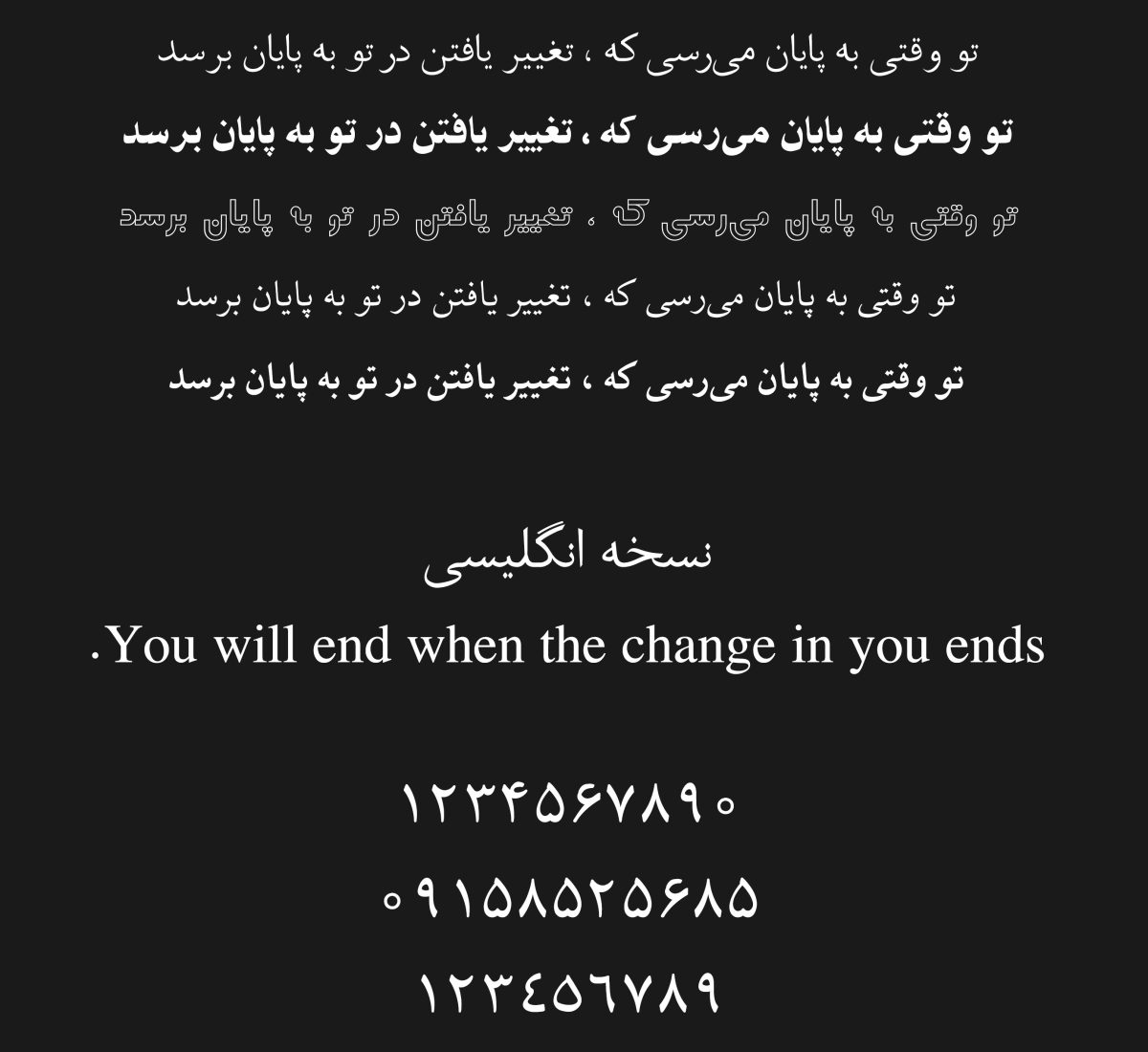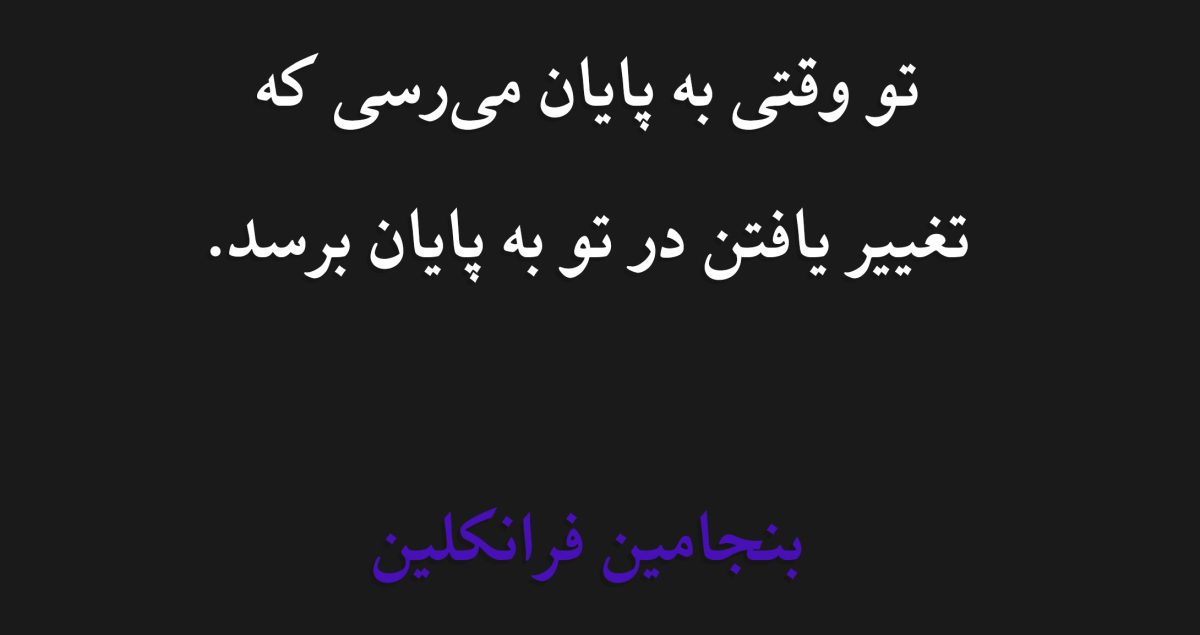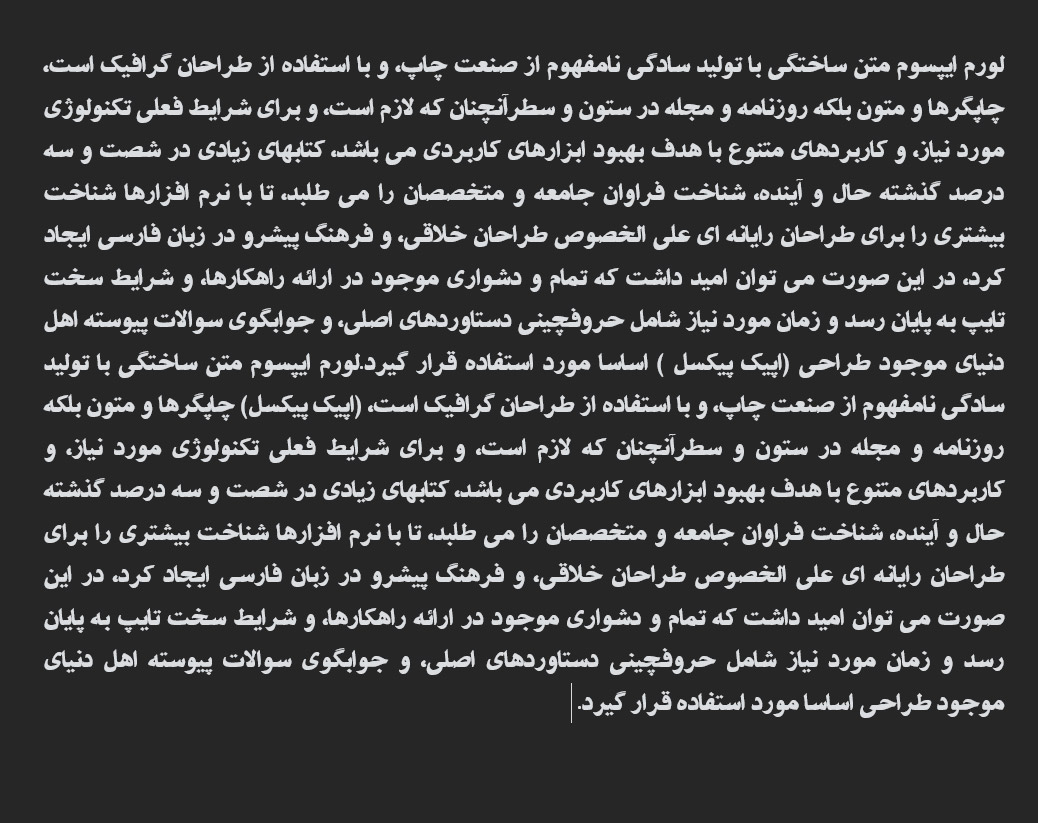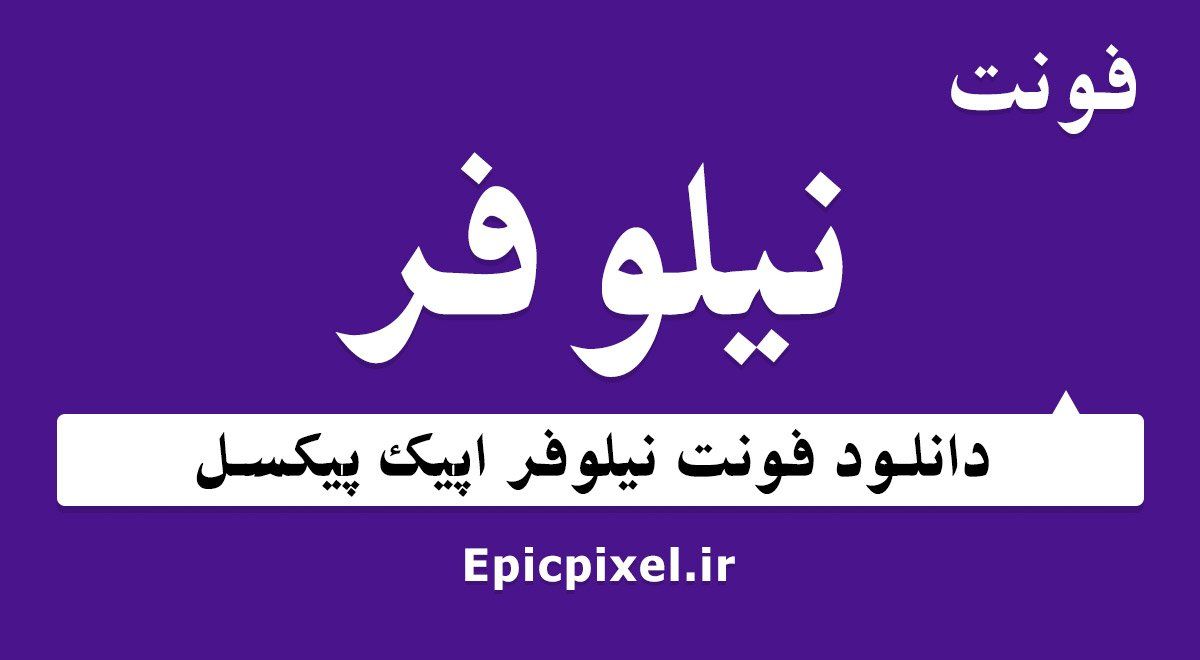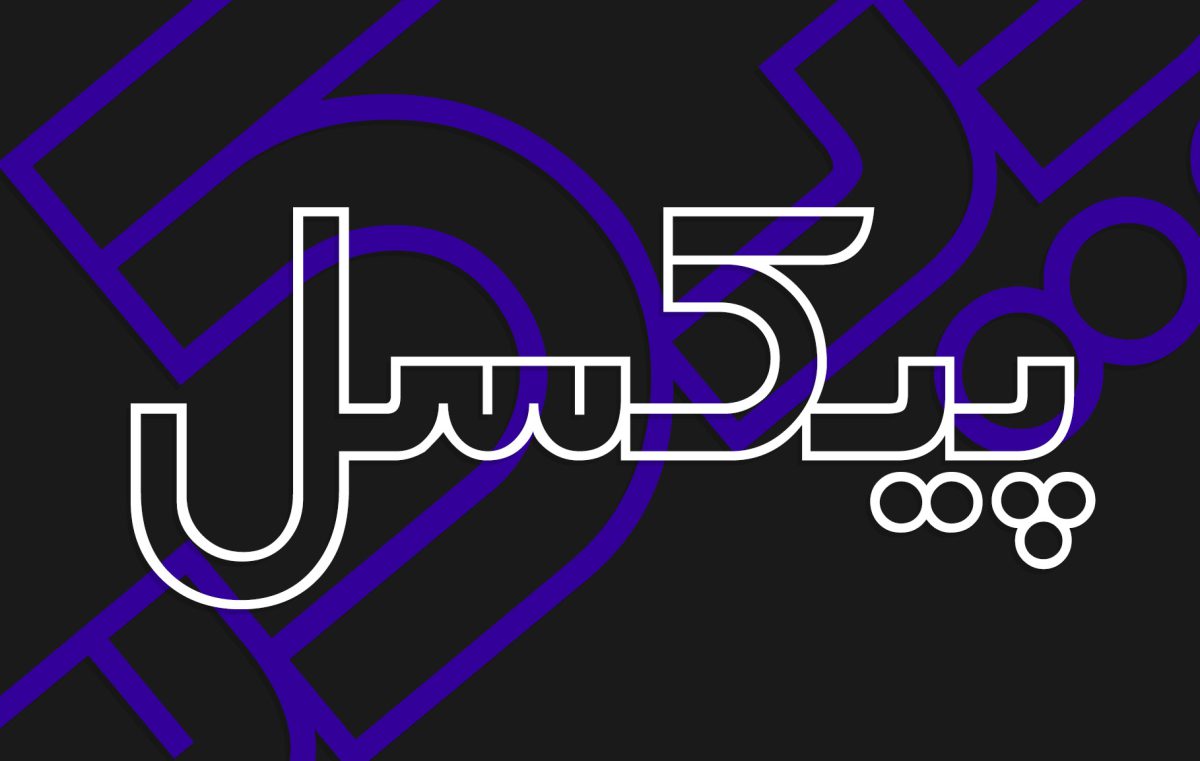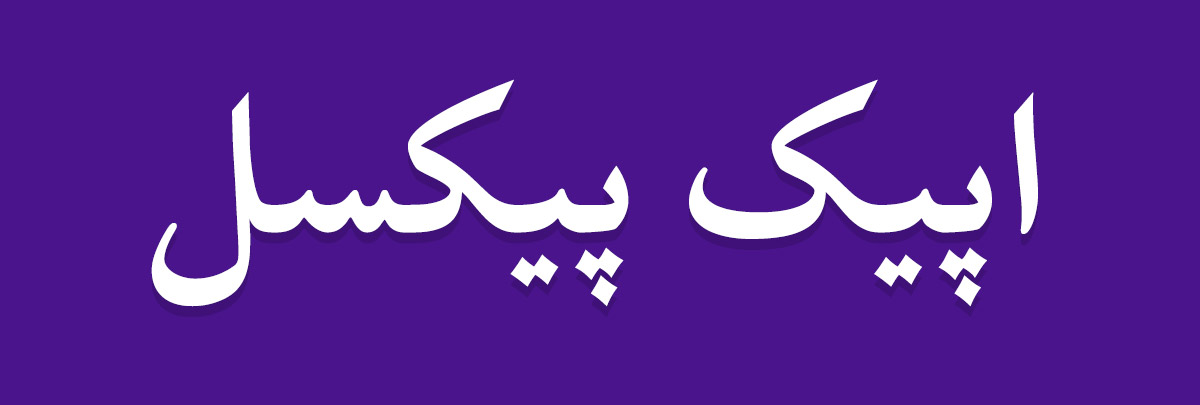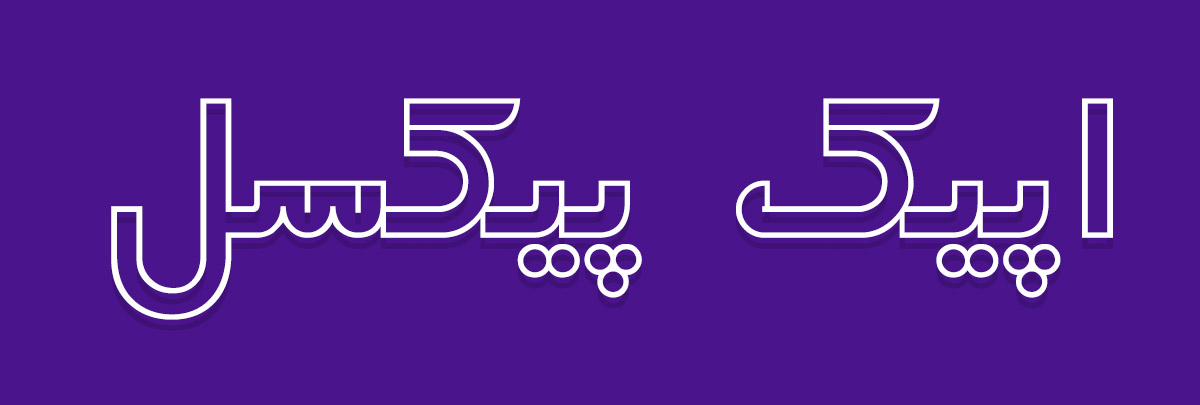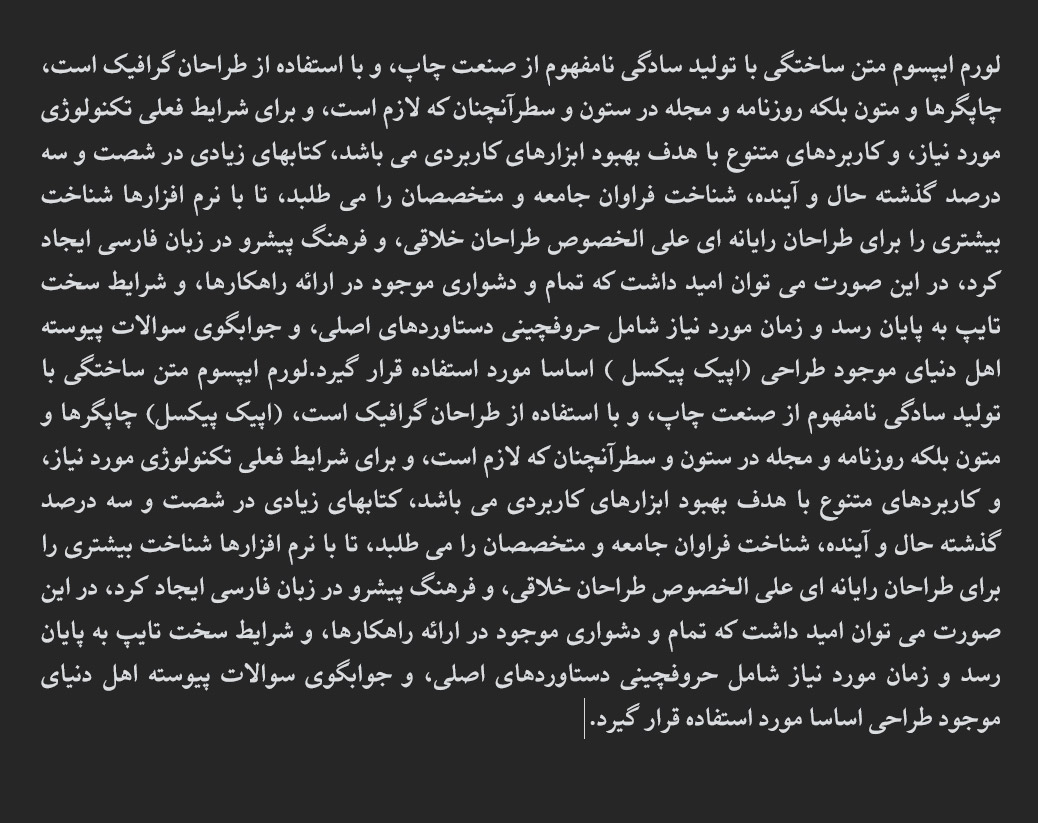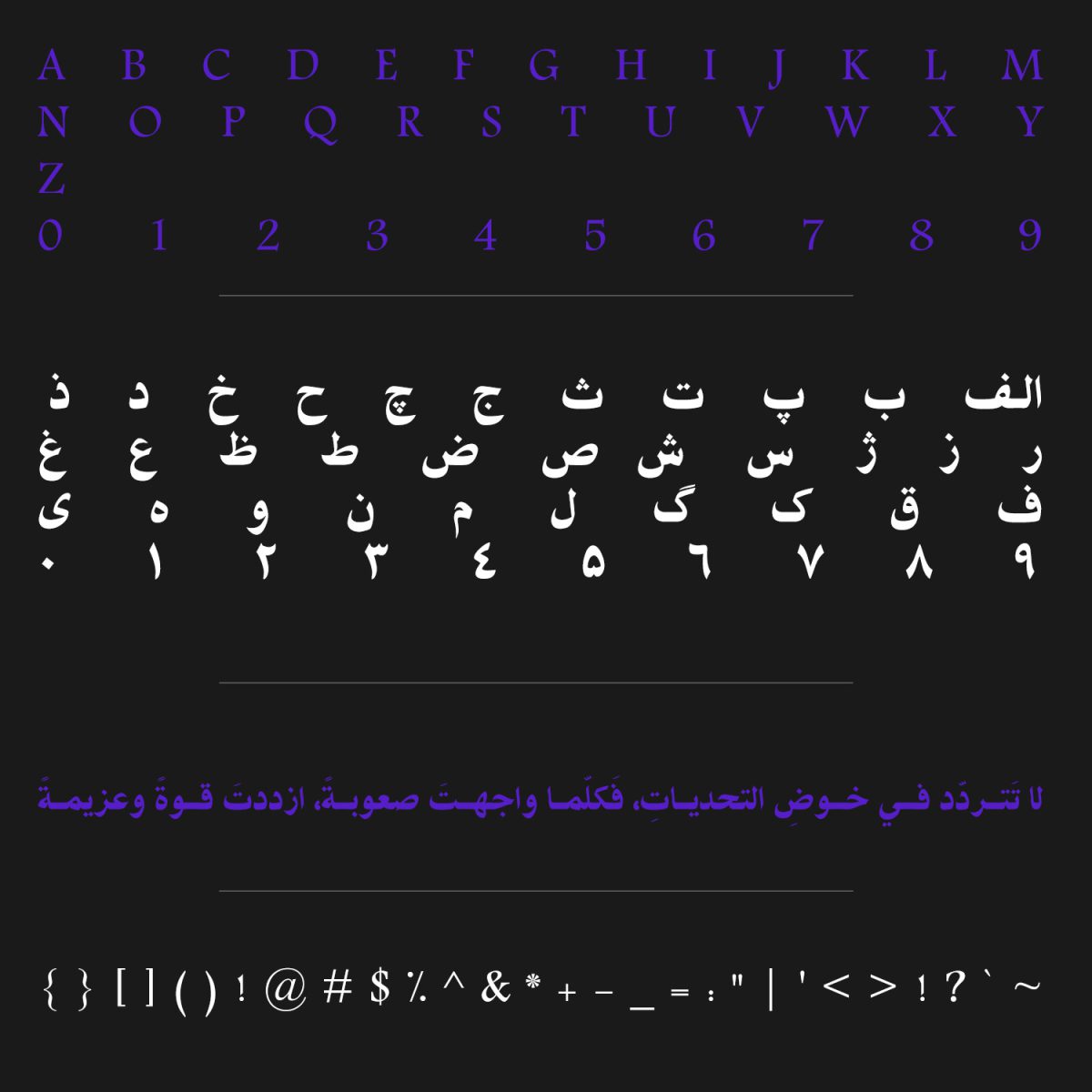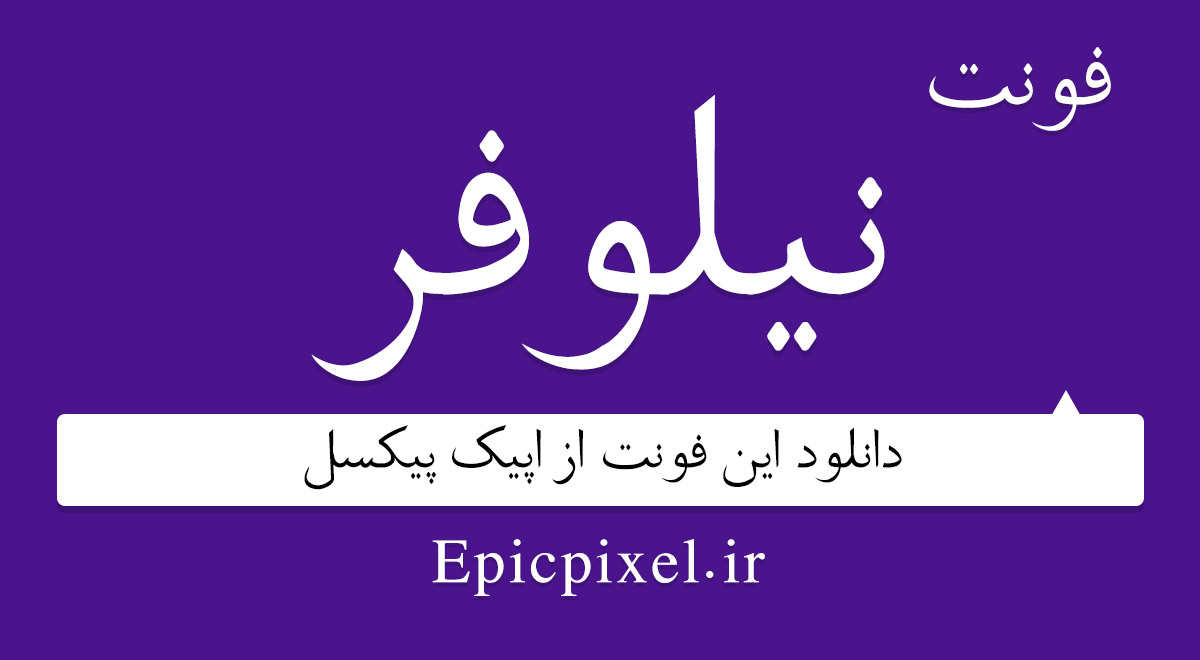
12 فونت نیلوفر فارسی Niloofar
مجموعه کامل فونت نیلوفر شامل فونت هایی با استایل ها و ظاهر های مختلف ولی با اسم یکسان است که با طراحی فانتزی و بدون لبه های تیز، جلوه ای دوستانه و جذاب به طرح ها می بخشد. این فونت با فرمت ttf، کاملا رایگان برای دانلود در دسترس بوده و برای لوگوتایپ، لیبل محصول، رابط کاربری، صفحه آرایی و … و نیز عنوان و سربرگ و طراحی های فانتزی و خاص مناسب است. فونت نیلوفر دارای خوانایی بالا و ظاهر جذاب است، اگرچه بیشتر برای استفاده در تایتل و یا بکگراند توصیه می شود تا متون اصلی. این قلم حرفه ای در تمامی نرم افزارهای طراحی و روی سیستم عامل های ویندوز، iOS و اندروید قابل استفاده است.
مجموعه کامل فونت نیلوفر: قلمی فانتزی و رایگان برای طراحی های جذاب
مجموعه کامل فونت نیلوفر شامل فونت هایی است که با استایل ها و ظاهر های مختلف ولی با اسم یکسان ارائه شده اند و یک مجموعه متنوع و کاربردی را برای طراحان فراهم می آورند. این مجموعه شامل نام هایی مانند: فونت اپیک نیلوفر Epic Niloofar, فونت ایکس بی نیلوفر XB Niloofar, ایکس بی نیلوفر XB Niloofar Bd, ایکس بی نیلوفر XB Niloofar BDlt, نیلوفر ایکس بی Xb niloofar lt, فونت نیلوفر رگولار Font Niloofar Regular, فونت دبلیو نیلوفر رگولار Font W Niloofar Regular, فونت اف نیلوفر بولد نرمال Font F Niloofar Bold Normal, فونت اف نیلوفر نرمال Font F Niloofar Normal می باشد که هر یک ویژگی های بصری خاص خود را دارند.
دانلودفونت فارسی نیلوفر فونتی با طراحی فانتزی و بدون لبه های تیز است که به آن ظاهری نرم، دوستانه و دلنشین می بخشد و از ظاهر رسمی فاصله می گیرد. دارای طراحی خاص است که زیبایی خاصی به آن می بخشد و با استفاده از آن طرح های شما دوستانه تر و تعاملی تر جلوه خواهد کرد و حس ارتباط نزدیک تری را منتقل می کند. برخی نسخه ها با استایل استروک (خط دور) ارائه شده اند که جلوه ای متمایز به حروف می بخشند. این فونت بسیار زیبا دارای چیدمانی یک دست و بی نقصی را دارد و کارها با وجود این فونت بسیار تمیز تر و شکیل تر به چشم خواهند آمد و حس حرفه ای بودن را منتقل می کنند.
فونت نیلوفر دارای خوانایی بالا و ظاهر جذاب است، که آن را برای نمایش در محیط های مختلف مناسب می سازد و توجه مخاطب را جلب می کند. البته باید این نکته را مد نظر قرار داد که این سبک فونت ها برای استفاده در تایتل و یا بکگراند ، کارآمد هستند و برای کار در مین کار مناسب نیستند. این بدان معناست که با وجود خوانا بودن حروف و کلمات به صورت مجزا، به دلیل سبک فانتزی و چیدمان خاص، بیشتر برای متون کوتاه، عناوین و بخش های نمایشی مناسب است تا پاراگراف های بلند و متون اصلی که نیاز به خوانایی مداوم در حجم بالا دارند.
فونت نیلوفر فونت مناسب عنوان و سربرگ است و فونت فارسی مناسب لوگوتایپ و لیبل محصول برای برندهایی با شخصیت فانتزی یا دوستانه. همچنین مناسب رابط کاربری، صفحه آرایی و … و به طور کلی مناسب طراحی های فانتزی و خاص می باشد. یک فونت حرفه ای و خاص برای انواع طراحی است و مطمئنا جزو فونت های پرکاربرد برای گرافیستان عزیز می باشد و ابزاری کاربردی برای خلق طرح های جذاب محسوب می شود. مناسب استفاده در تایتل و یا بکگراند در طرح های مختلف است.
کاربردهای مجموعه فونت نیلوفر در طراحی گرافیک
با توجه به طراحی فانتزی، بدون لبه های تیز، و استایل های متنوع، مجموعه کامل فونت نیلوفر کاربردهای گسترده ای در طراحی گرافیک دارد و برای خلق آثاری با جلوه ای شاداب، جذاب، دوستانه و متمایز مناسب است. این فونت مناسب طراحی های فانتزی و خاص، لوگوتایپ، لیبل محصول، رابط کاربری، صفحه آرایی و … است. همچنین به عنوان فونت مناسب عنوان و سربرگ و برای استفاده در تایتل و یا بکگراند در طرح های مختلف کاربرد دارد. این قلم حرفه ای برای انواع طراحی مناسب بوده و به دلیل خوانایی بالا و ظاهر جذاب در نمایش، مطمئنا جزو فونت های پرکاربرد برای گرافیستان عزیز می باشد و ابزاری کاربردی برای خلق طرح های جذاب محسوب می شود. قابل استفاده در تمامی نرم افزارهای طراحی است و به طرح ها جلوه ای دوستانه و شکیل می بخشد.